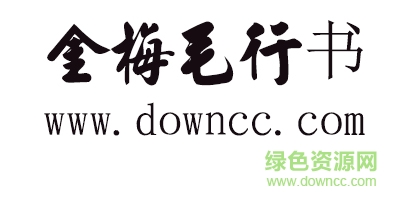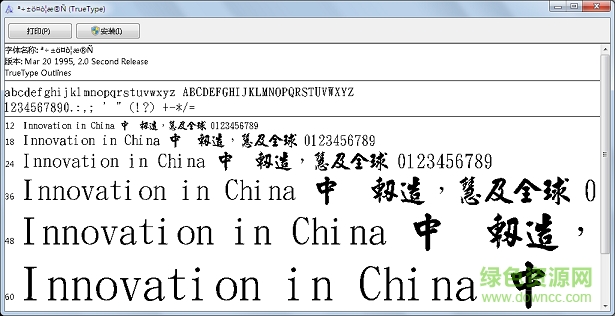
金梅毛行書(shū)體是一款免費(fèi)的金梅字體文件!這款字體兼具了毛筆字體和行書(shū)字體的風(fēng)格特征,輸出的文字不要太美觀!適用范圍廣,喜歡的用戶(hù)歡迎下載使用。
金梅毛行書(shū)體結(jié)合了行書(shū)字體和毛筆字體的特點(diǎn),給人感覺(jué)非常飄逸輕柔。多用于設(shè)計(jì)作品使用!快來(lái)綠色資源網(wǎng)下載吧!